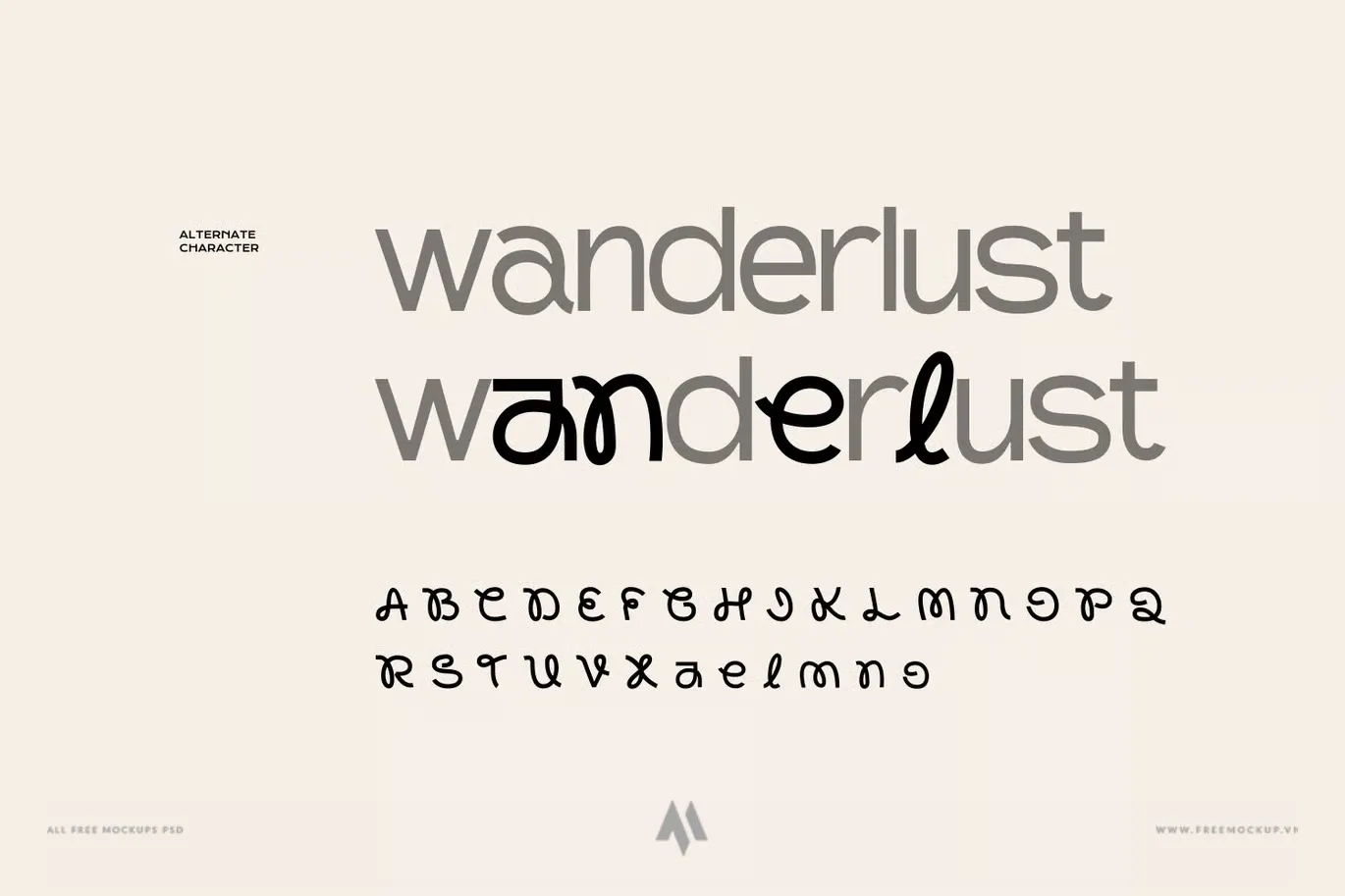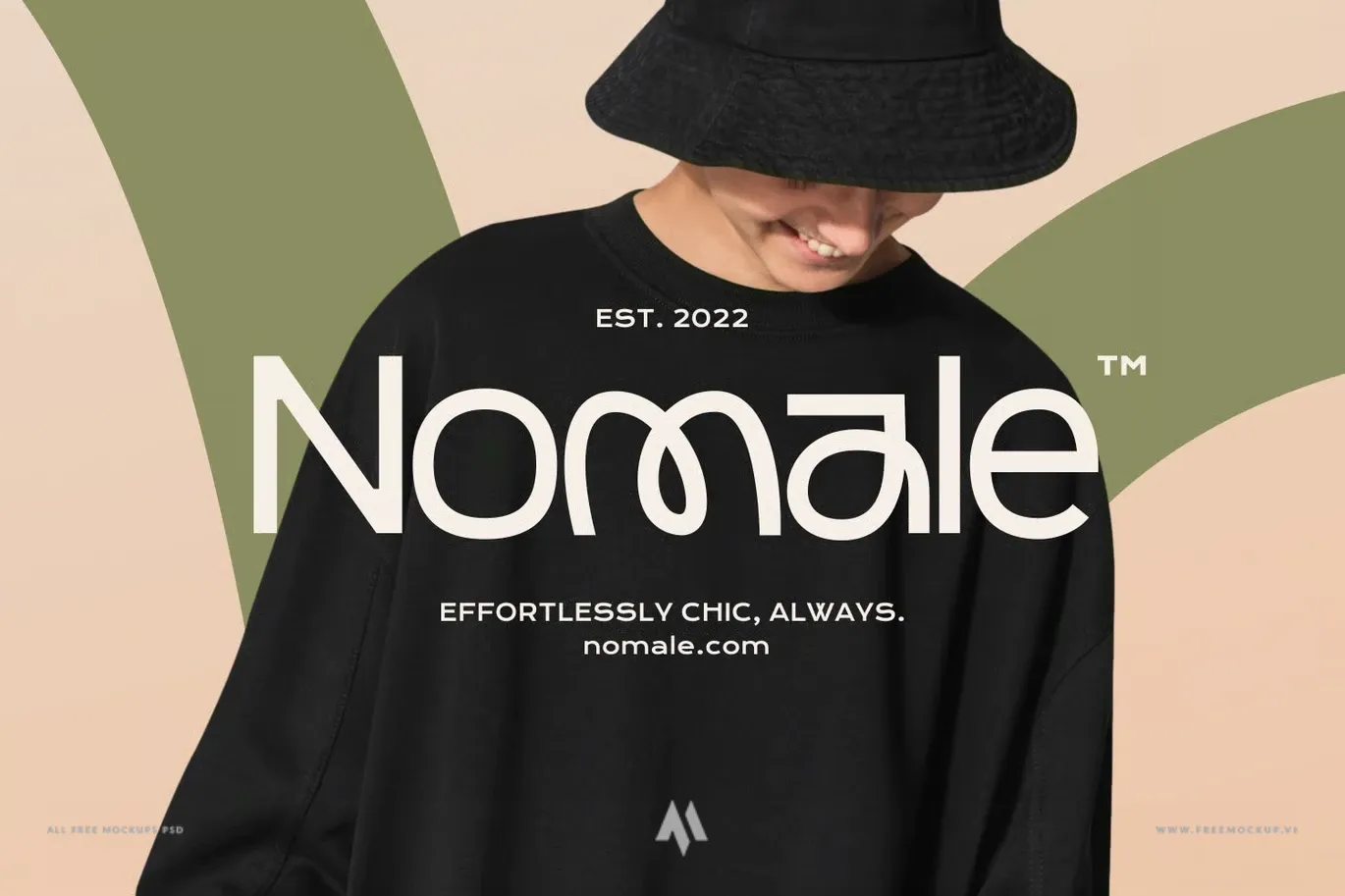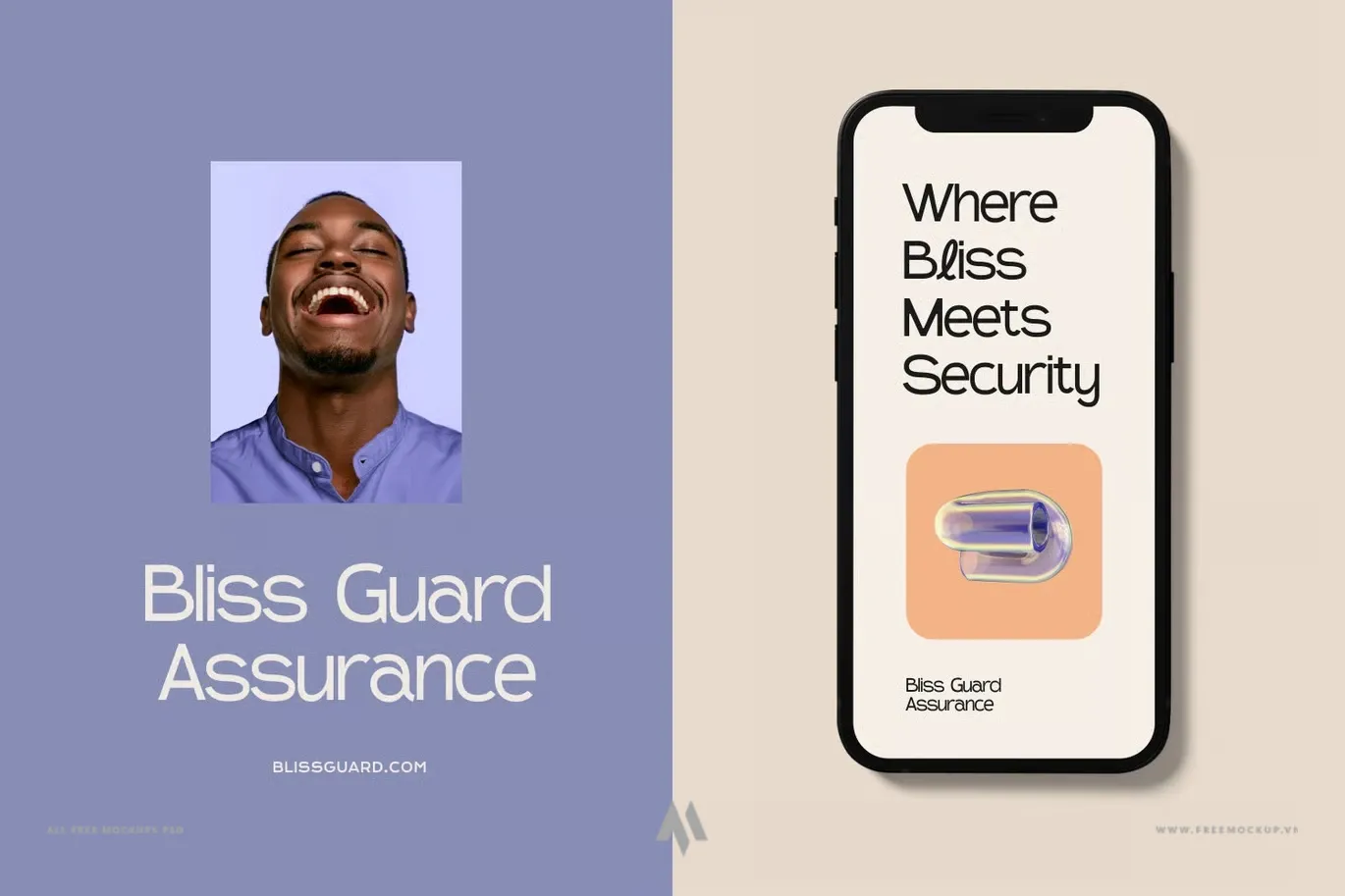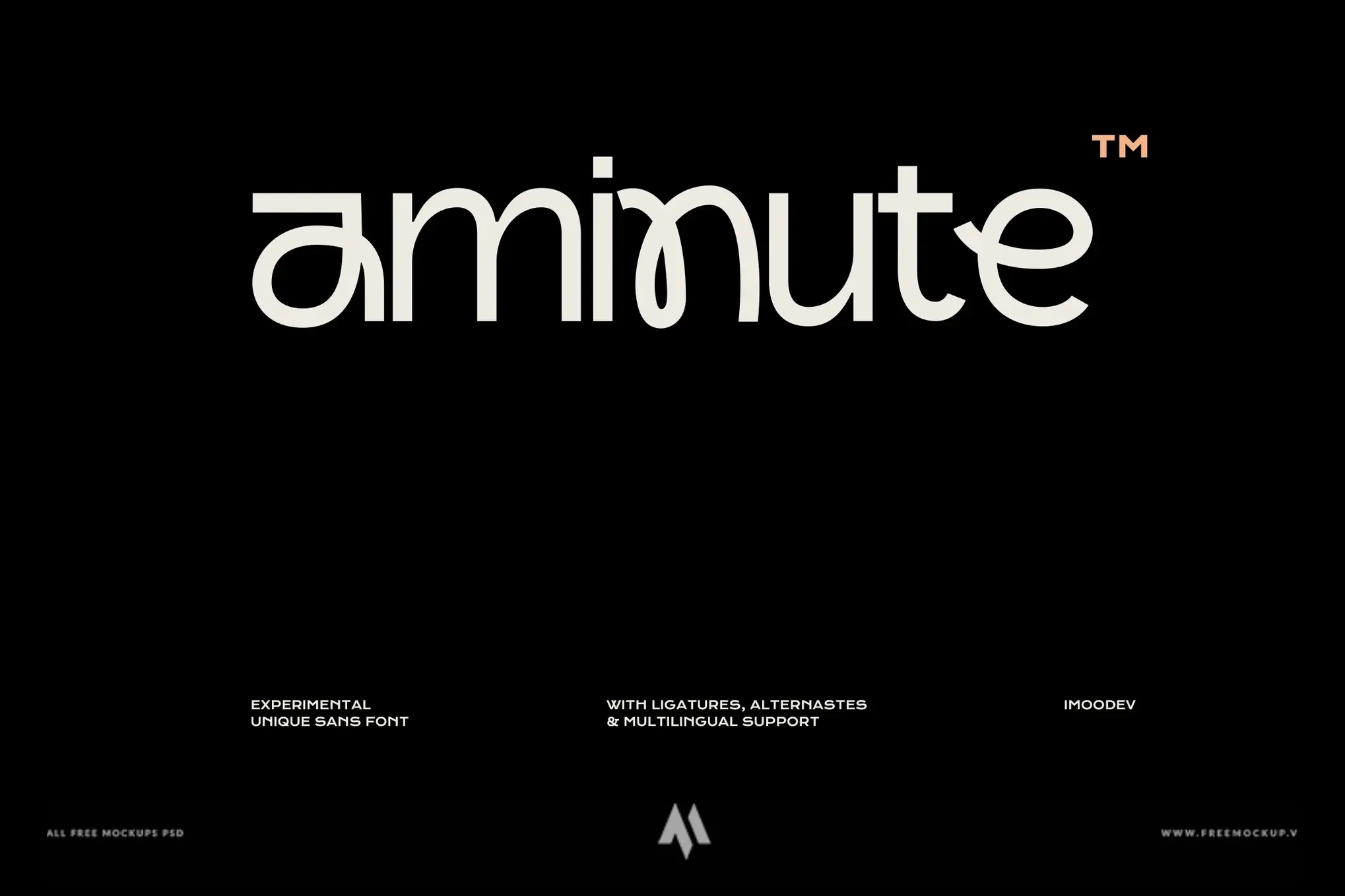
Font Aminute Việt hóa miễn phí
aminute Việt hóa miễn phí
Font Aminute Việt Hóa là bộ font chữ không chân mang tính thử nghiệm (Experimental Sans-Serif) đầy tính nghệ thuật, nổi bật với cấu trúc con chữ phá cách, ngộ nghĩnh và đầy ngẫu hứng. Sở hữu sự kết hợp hoàn hảo giữa nét hiện đại gọn gàng và những biến thể ký tự độc đáo, Aminute là công cụ đắc lực để tạo nên điểm nhấn thị giác sáng tạo, khác biệt cho mọi ấn phẩm đương đại.
Thiết kế thử nghiệm độc đáo: Dung hòa khéo léo giữa phong cách Sans-Serif hiện đại, đường cong mượt mà ở bộ ký tự cơ bản cùng các ký tự thay thế (Alternates) mang đậm chất nghệ thuật, tinh nghịch và mới lạ.
Kho ký tự nối & biến thể phong phú: Tích hợp nhiều ký tự ghép (Ligatures) và ký tự mở rộng linh hoạt, giúp bạn dễ dàng biến hóa bố cục tiêu đề theo phong cách Art Deco, Retro hay Futuristic.
Tối ưu hiển thị đa kích thước: Cân đối hoàn hảo ở cả định dạng chữ hoa (uppercase) lẫn chữ thường (lowercase), giữ trọn độ sắc nét từ kích thước hiển thị lớn đến chi tiết phụ.
Chuẩn hóa tiếng Việt hoàn chỉnh: Toàn bộ hệ thống ký tự và dấu tiếng Việt được trau chuốt tỉ mỉ, tương thích mượt mà trên Adobe Photoshop, Illustrator, InDesign, Figma và Canva.